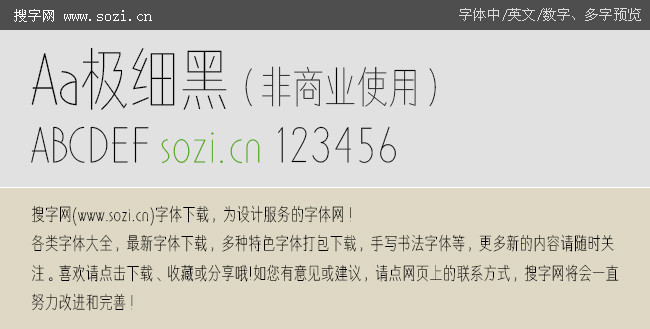
Aa極細(xì)黑(非商業(yè)使用)
搜字網(wǎng)給大家提供一款A(yù)a極細(xì)黑(非商業(yè)使用)中文字體下載,該字體較為纖細(xì),字體瘦長,干凈利落。適合海報(bào)設(shè)計(jì)、包裝畫冊等宣傳廣告等應(yīng)用(此字體為個(gè)人非商用版,商用可以聯(lián)系QQ:1006760504)。